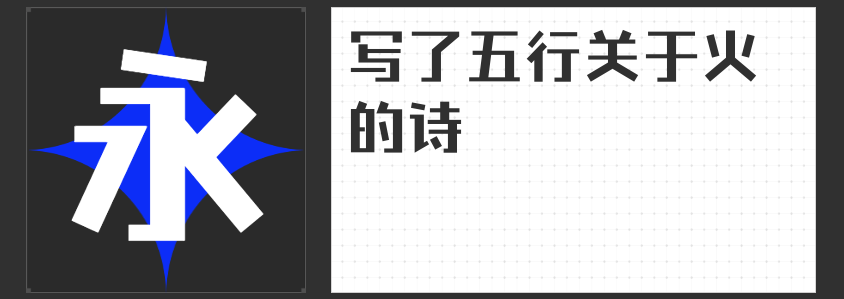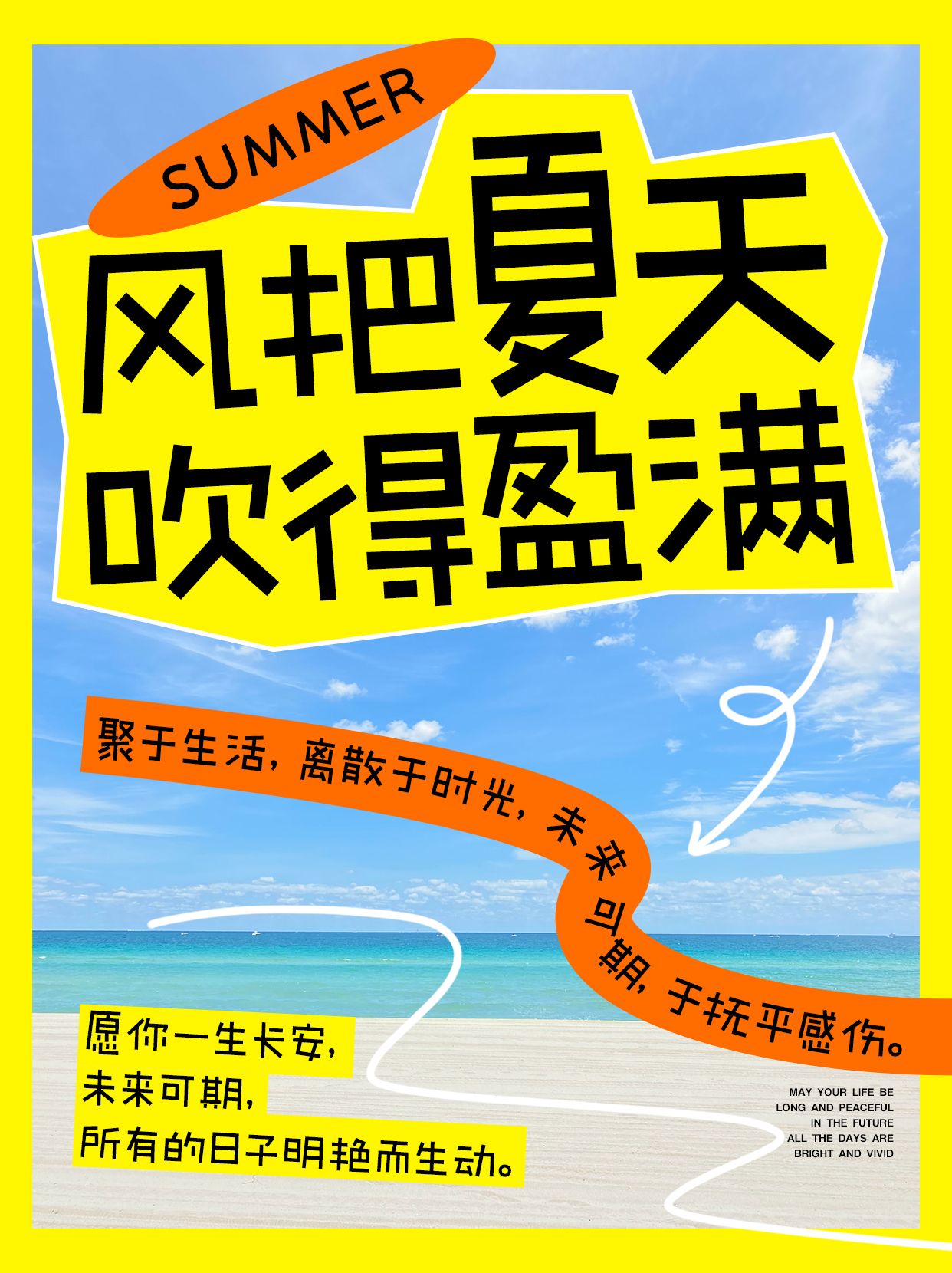
让标题瞬间吸睛!四款个性标题字体精选指南
在视觉传达中,标题字体是抓住观众注意力的第一触点。以下四款标题字体,以独特的设计语言赋予文字戏剧张力,让每一次排版都成为视觉焦点。
1.造字侠伏魔简繁 传神
这款字体以浓墨重彩的笔触展现书法魂韵,粗细对比强烈的笔画如刀刻斧凿,勾挑捺画极具张力。中正的架构中暗藏收放自如的巧思,单字如武将亮剑,适合传统与现代碰撞的场景——电影海报的片名、武侠小说的封面标题,或是国风品牌的视觉主标,瞬间传递力量感与文化厚度。
2. 高手庆科竞速体 常规
高手庆科竞速体以直线美学重构汉字骨架,瘦长字形如利箭破空。去钩后的斜切处理与平切起收笔,在工整中暗藏速度感。均匀布白与紧凑中宫赋予其科技感,尤其适合科技产品发布会主视觉、电竞游戏界面标题,或是需要传递现代锐气的商业海报,让文字如赛车般冲破视觉终点线。
3. 字恋狂漫野 鸣风
这款字体将手写温度注入几何框架,张弛有度的结构配合通透布白,单字大小错落如诗行韵律。去钩处理与断开式笔画设计,在简洁中保留人性温度,适合音乐海报、文艺展览标题,或是需要营造轻松氛围的杂志封面,让版面随文字节奏起舞。
4. 励字钧线黑简 大黑
励字钧线黑简 大黑以全直线设计挑战传统,锐角转折如刀锋出鞘。摒弃装饰的纯粹主义理念,使其既能作为奢侈品广告的冷峻标题,亦可化身艺术展览的先锋宣言。灰度均匀的视觉特性,在巨幅广告牌或数字屏幕中均能保持强烈存在感,成为现代极简设计的点睛之笔。
这四款字体如同四种视觉人格:或豪迈、或冷峻、或灵动、或锐利。它们突破常规字体的框架,用设计语言讲述独特故事。当需要让标题从背景中跃然而出时,不妨从这些字体中寻找灵感——它们不仅是文字容器,更是视觉舞台上的主角。